<에릭 길 : 타이포그래피에 관한 에세이> : 타이포그래피 고전 중의 고전
『에릭 길: 타이포그래피에 관한 에세이(An Essay on Typography)』는 1931년 첫 출간과 함께 ‘다시 나오기 어려운 최고의 책’이라는 평가를 받았다. 에릭 길이 전성기에 써낸 이 책은 독선적으로 호언하고 늘 인문적이었던 길의 생각을 보여준다. 길은 이 책에서 모양과 정렬, 기능 등 글자뿐 아니라 산업사회에서 인간의 역할에 관해 선언적으로 진술한다. 이는 산업주의와 수공예라는 두 세계를 묘사하고, 한계를 밝히기 위해서였다.
글자에 관한 길의 생각은 오늘날까지 유효하다. 1931년 이 책이 출간되고, 30여 년 동안 글자 기술은 엄청나게 바뀌었다. 하지만 길의 작업을 비롯해 글자는 1931년과 크게 다르지 않다. 양끝을 맞추지 않은 글줄과 좁은 글자사이 공간, 띄어쓰기, 넓은 글줄사이 공간 등 오늘날 널리 쓰이는 방법이 이미 등장한다. 이뿐 아니라 실무적이면서 논쟁적인 모습, 노동과 영혼에 대한 깊은 관심, 과정만큼 결과에 집착한 인간 길의 면모가 고스란히 드러난다. 이 책은 길이 평생 몰두한 글자 실무를 다룬다. 이 이유만으로 독자가 관심을 둘 가치가 있다.
이 책은 길의 진수를 담은 책으로, 길의 이상주의와 실용주의, 일상 작업에 관한 기독교적 시각을 보여준다. 실무적 조언 사이사이는 윤리적 교훈과 격언으로 채워진다. 두 평행선은 단조롭거나 장식적인 글자 속으로 빠져들고, 기독교식 결혼과 잉크 이야기에서 평범과 고통의 미덕을 향한 찬사로 이어진다. 디자이너는 “셀 수 없이 많은 ‘살아야만 하는’ 이유”를 위해 살아야 하듯 길은 상업 활동을 겨냥한 비판을 자제하지 않고, 이따금 불공평한 진술도 마다하지 않는다. 하지만 이 덕에 독자는 타이포그래피뿐 아니라 다양한 관점에서 길에게 다가갈 수 있다.
24쪽, 「시간과 장소의 구성」 가운데
“큰 사업이나 대량생산 체제와 경쟁할 수는 없지만, 사람들은 짬을 내 주머니칼로 깃펜을 깎고, 여기서 즐거움을 찾을 것이다. 수공예가와 수공예품은 사라지지 않을 것이다.”
39쪽, 「글자」 가운데
“글자는 일종의 추상적 모양이다. 사람들은 이 모양에 감도는 신비로운 매력에 이끌렸다. 글자는 제도나 권력 눈치를 보지 않고, 아름다운 모양에 따라 다듬어졌다. 예술과 사회적 규범은 섞일 수밖에 없지만, 글자 예술은 다른 예술에 비해 순수하다. 중국인처럼 고도로 문화적이고 이성적인 사람들에게 서예와 비문 조각의 높은 경지를 볼 수 있다. 중국인에게 좋은 서예 작품은 영국인에게 그림보다 훨씬 귀하다. 영국인이 수프 끓이는 기계를 끔찍이 여기듯 말이다.”
79쪽, 「타이포그래피」 가운데
“일부러 끔찍하게 하거나 사람들을 속이려는 게 아니라면, 산업주의 타이포그래피는 단순해야 한다. (수천 가지 잉크와 종이, 인쇄기, 숙련된 디자이너가 디자인하는 기계적 과정 등) 엄청난 자원에도 이는 생명력이나 화려함과 멀어지고, 장식은 사라질 것이다. 꽃은 이런 흙에서 피지 않는다.”
109쪽, 「책」 가운데
“네 가지 판형이 있으면, 일반적으로 글자크기도 네 가지가 필요하다. 휴대용 책은 지면이 그리 넓지 않아 본문 글자크기는 8포인트 정도가 적절하다. 이보다 큰 책은 사람 팔 길이와 시력을 고려해 1012포인트 정도가 알맞다. 탁자나 독서대에 놓는 책은 일반적으로 더 먼 곳에서 읽으므로 14포인트나 18포인트, 또는 이보다 더 커야 한다. 하지만 이는 반드시 지켜야 하기보다 널리 쓰이는 규격으로 보면 된다.”
128쪽, 「그런데 왜 글자를?」 가운데
“시곗바늘을 되돌릴 수는 없다. 하지만 시간이 흘러갔다는 사실과 우리가 여전히 고대 영국인인 척할 수 없다는 사실을 알아야 한다. 글자는 시대의 산물이다. 철자법과 표음식 철자법, 모든 규칙은 설 자리가 없다. 오늘날 글자를 개선하는 유일한 길은 이를 없애는 것이다.”
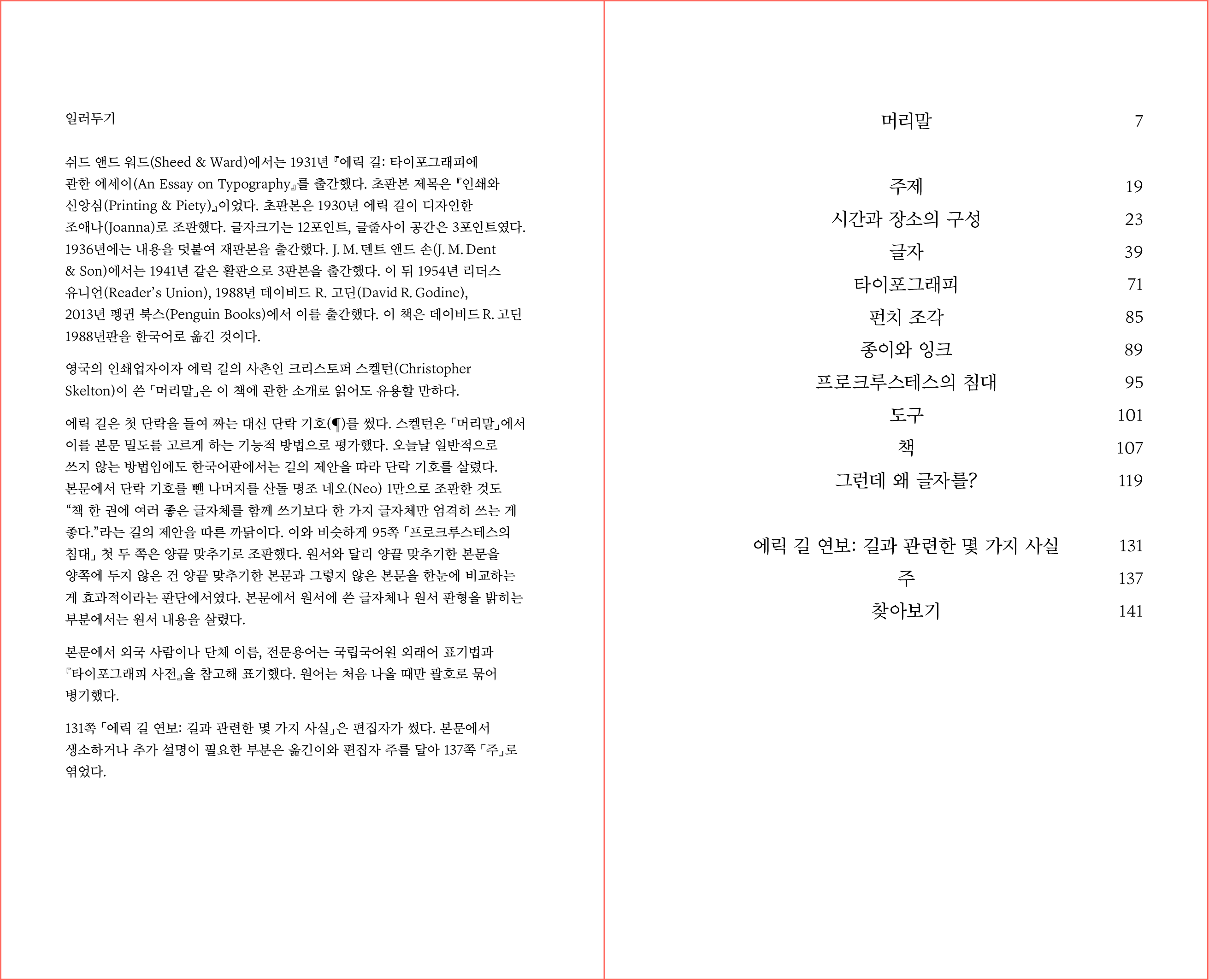
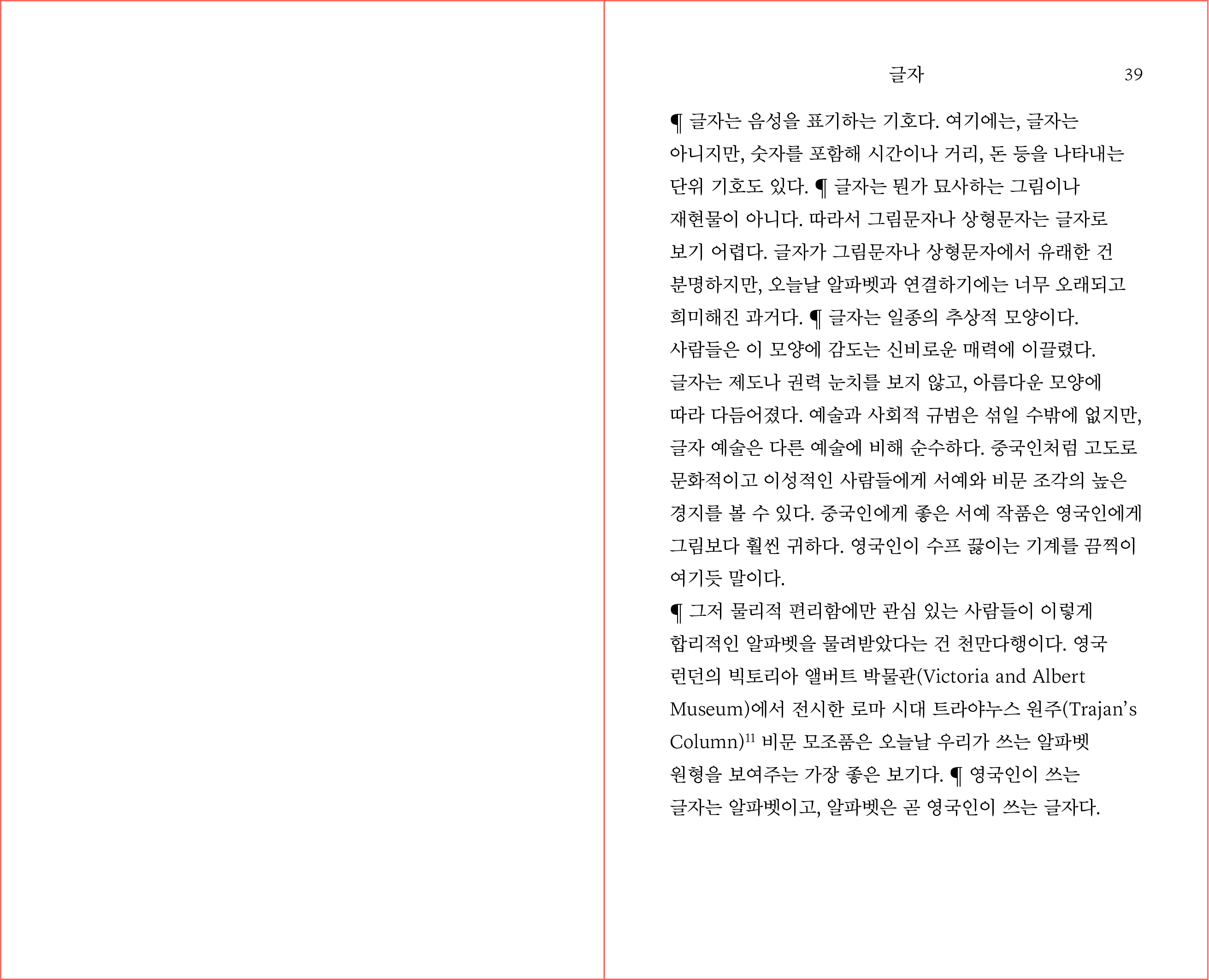
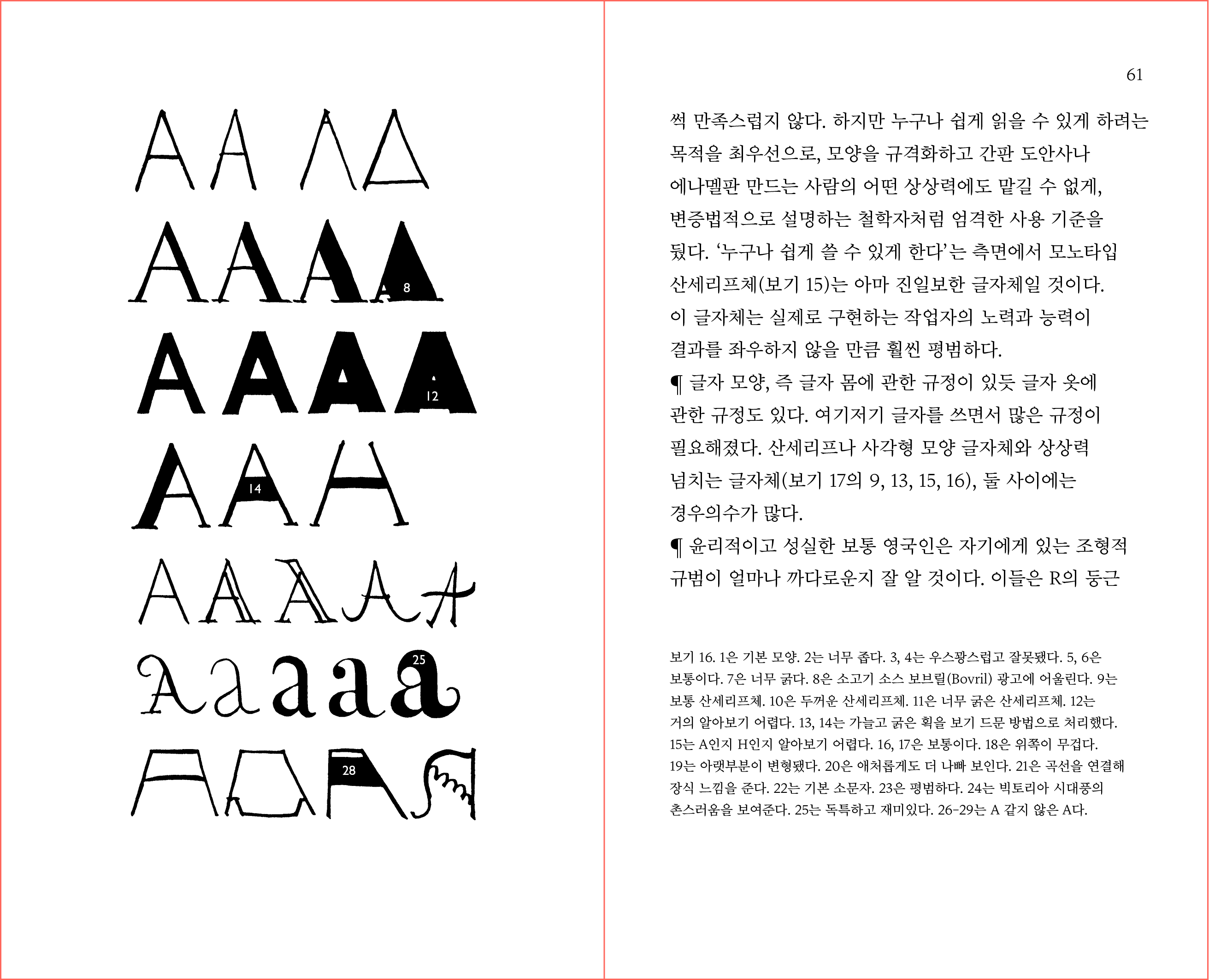
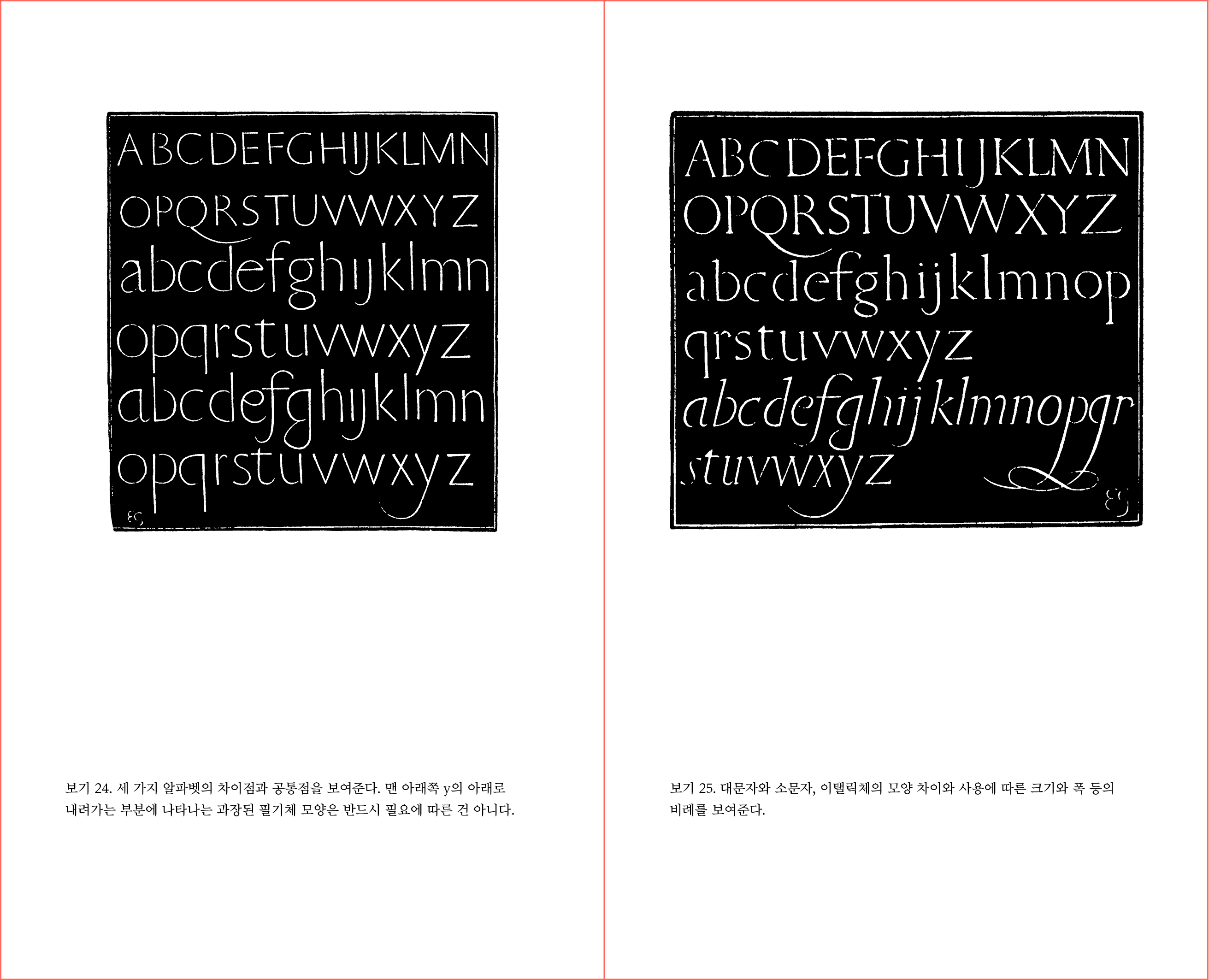
에릭 길(Eric Gill)
1882년 영국 서식스 스테이닝에서 태어났다. 브라이튼에서 어린 시절을 보내며 글자와 건축에 관심과 재능을 보였다. 센트럴 미술 공예 학교(Central School of the Art and Crafts)에서 영국의 글자체 디자이너 에드워드 존스턴(Edward Johnston)을 사사하며 글자 조각을 시작했다. 길이 1928년에 디자인한 글자체 길 산스(Gill Sans)는 산세리프체의 간결함과 세리프체의 우아함을 동시에 지녔다고 평가받는다. 1903년 장인으로 독립해 1940년 세상을 뜰 때까지 조각과 판화, 철학, 글자체 디자인 등 다양한 분야를 섭렵했다. 길은 평생 급진적 진보주의자이자 사회 개혁가로 자기 철학을 작업에 구현하려 애썼다.
이 책은 에릭 길의 주장을 철저히 따르고 있다. 책 한 권의 한가지 글자체만 쓰는 게 좋다는 말에 따라 단락기호를 제외한 모든 본문을 산돌 명조 Neo로만 조판했다.